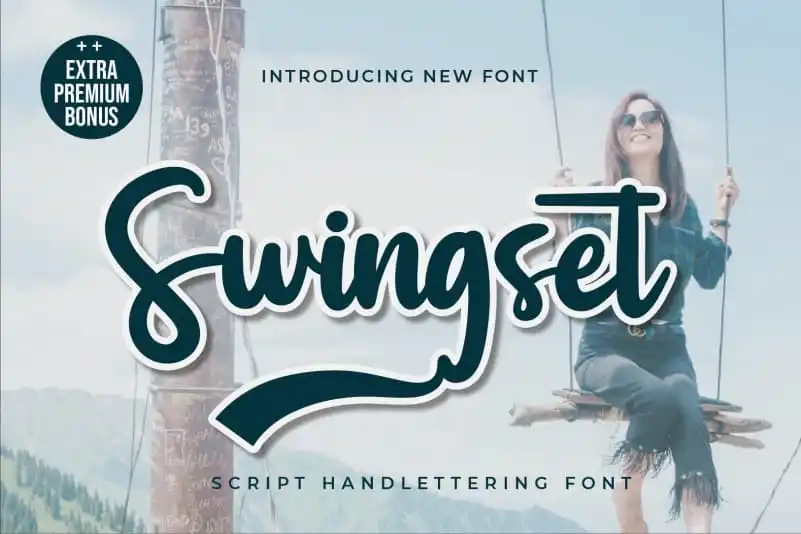
Swingset Script Font – Fonte Grátis
Swingset Script Font
Swingset Script Font é uma opção perfeita para designers amantes do estilo vintage que procuram algo um pouco mais elaborado, mas não tão formal quanto outros estilos serifados. Inspirada no tipo de texto clássico, esta fonte traz sua própria personalidade única a qualquer projeto de design. Se você está buscando novas maneiras de enfeitar suas postagens em Instagram ou adicionar um toque sofisticado e elegante a seus projetos DIY, Swingset Script Font é definitivamente o que você precisa. Suas linhas elegantes e arredondadas permitem que qualquer ideia criativa seja transformada em arte perfeita. Seja para criar uma identidade visual única ou para dar um toque especial a sua próxima peça de decoração, Swingset Script Font é definitivamente um ponto de vista a ser adotado.